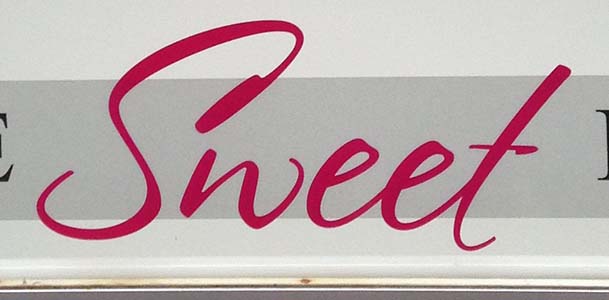
Nette Handschrift - leider nur wenig Buchstaben
Kann mir jemand helfen, diese Font zu finden - mir kommt sie zwar irgendwie bekannt vor, aber ich kann sie nicht zuordnen... Danke